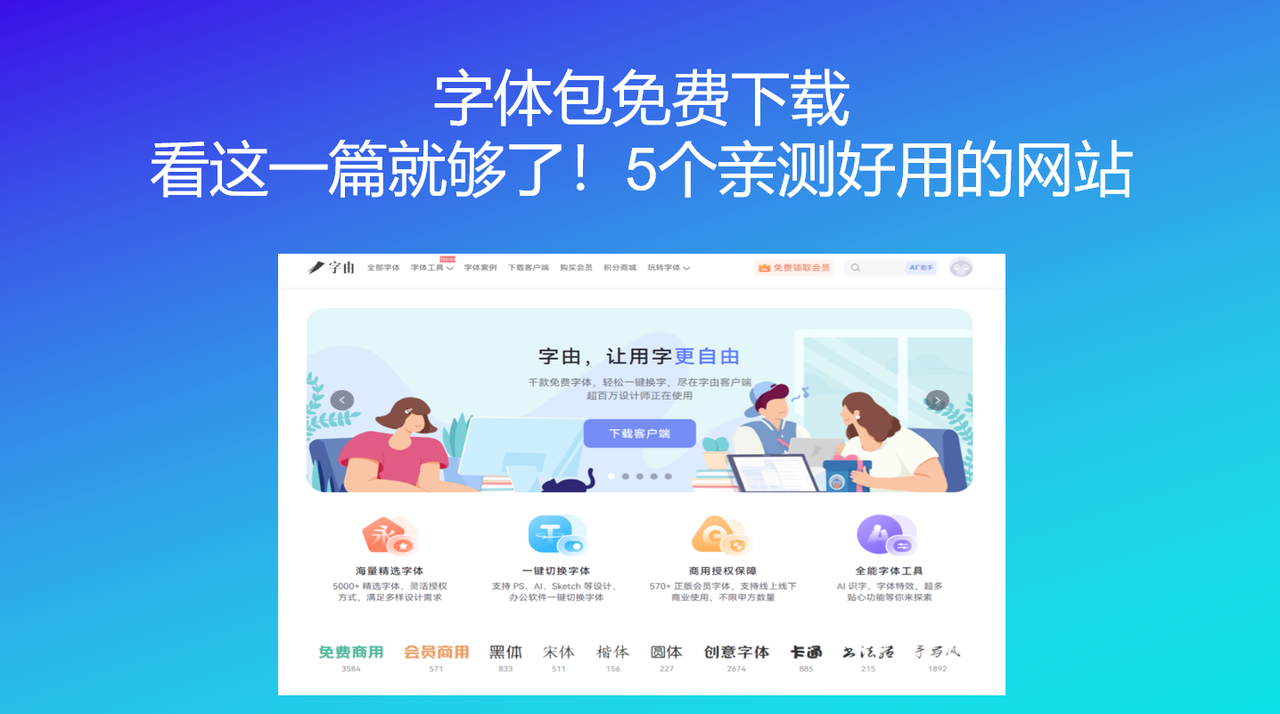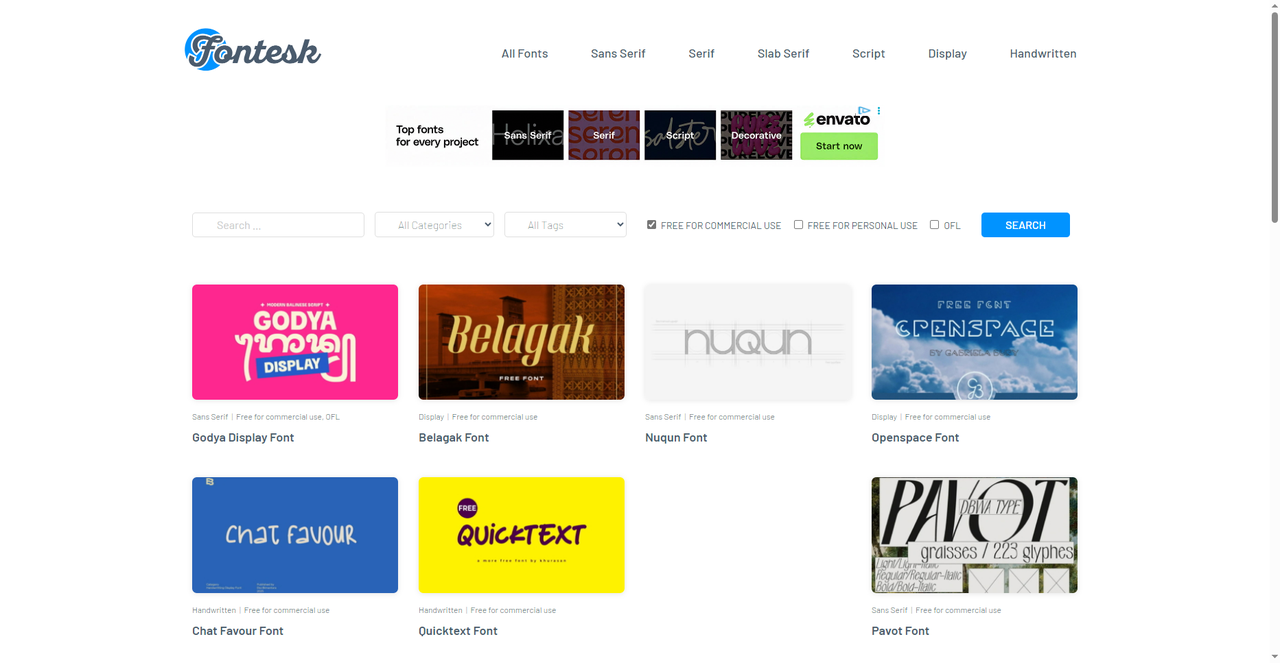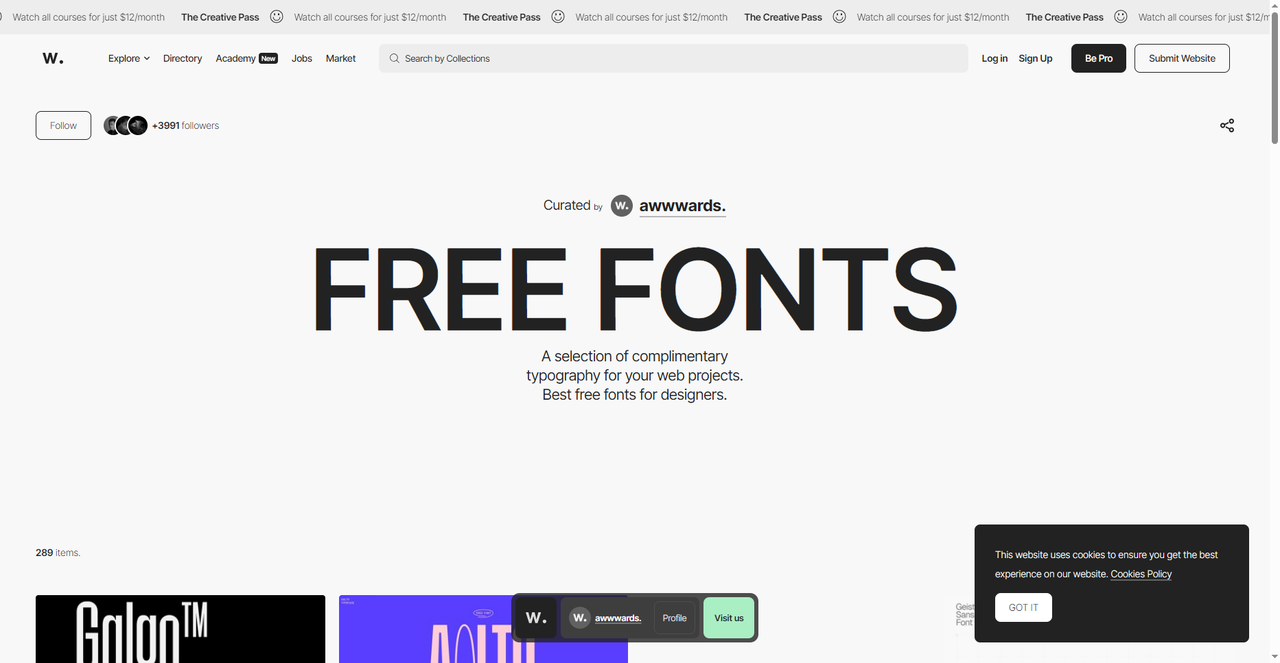
字体包免费下载,看这一篇就够了!5个亲测好用的网站
如果你是做设计的,那么我相信你的硬盘里一定会有专门放字体的文件,不论是自己积累的还是从零散网站里下载的字体,大大小小总应该有好几个 G 了,因为我就是这样。每次真正要用字体的时候需要翻半天并且还不能很准确地找到合适的字体。有时候去网上搜索字体,下载下来以后才发现“仅限个人练习使用”,更是白高兴一场。其实字体包免费下载的资源有很多,关键是找对地方。今天我就整理了 5 个亲测好用的字体包免费下载网站,都是我一个一个踩坑总结出来的,需要的话直接收藏,以后找字体不用再到处翻了!
今天要介绍的第一个字体包免费下载网站是字由。它和普通字体下载网站最大的不同,是它直接把 5000 多款字体打包成了一个“超级字体包”——你不需要一个一个下载、安装,打开客户端就能用。字由所涵盖的字体包本身就已经足够丰富,因为其内置了 5000 多款精选字体,其中超过 3500 款是免费可商用的,每一款都标注了授权类型,用起来特别省事。如果你是团队管理者,开通团队/企业会员后,可以创建团队专属字库。管理员可以上传本地字体或添加字由字体至团队字库,上传后所有成员都能共同使用。对于设计团队、广告公司来说,这个功能能统一团队用字规范,避免每个人各用各的字体导致作品风格不统一。不过就算不开通会员你也依旧可以享用很多优质免费字体包。
2、Fontesk
Fontesk 是一个专门收集免费字体的平台,它的免费商用字体版块规模非常可观——目前收录了超过 6500款 真正免费可商用的字体。并且网站内提供的筛选栏非常便捷,你可以按风格、按标签,甚至是可以按授权类型来筛选,这种非常细致的分类能够帮你快速锁定想要的字体风格。除了常规的风格分类,Fontesk 还有很多“情绪标签”——比如“Edgy”(前卫)、“Bouncy”(活泼)、“Romantic”(浪漫)、“Cyberpunk”(赛博朋克),如果你在做一个有特定调性的项目,但是不知道用什么样的字体,可以试试 Fontesk 里面的字体包,下载也十分方便,安装就可以使用。
3、Awwwards
Awwwards 是全球知名的网页设计奖项平台,每天都会评选出优秀的网站设计。很多人不知道的是,Awwwards 专门整理了一个 “Free Fonts”字体包,收录了289款适合网页项目的免费字体。这个合集里的字体都是经过 Awwwards 团队挑选的,风格偏向现代、简约、有设计感。比如 Geist by Vercel、Pangram Sans Rounded、PP Mori、Harmond 等,都是当下网页设计圈比较流行的字体。点击任意一款字体,可以看到它在网页上的应用效果,如果你在做网页设计或者是 UI 设计,需要一些现代感强、风格明显的字体包,那么Awwwards 的免费字体包值得收藏。
4、Free Typography
Free Typography 是一个专注于分享免费字体和设计资源的博客型网站。从首页可以看到,它主要提供独家免费字体下载、字体推荐和设计访谈等内容。网站的主要特点就是会定期更新最新免费字体,比如首页展示的 Renesnip Sans(由设计师 Jorn Slotboom 提供)和 Victorian Decade(来自 Fontsgood),都是独家下载资源。最主要的是,Free Typography 还有一个很实用的功能——邮件订阅。输入邮箱后可以收到免费的博客更新和独家免费字体,只对订阅用户开放。如果你不想错过好资源,可以考虑订阅。
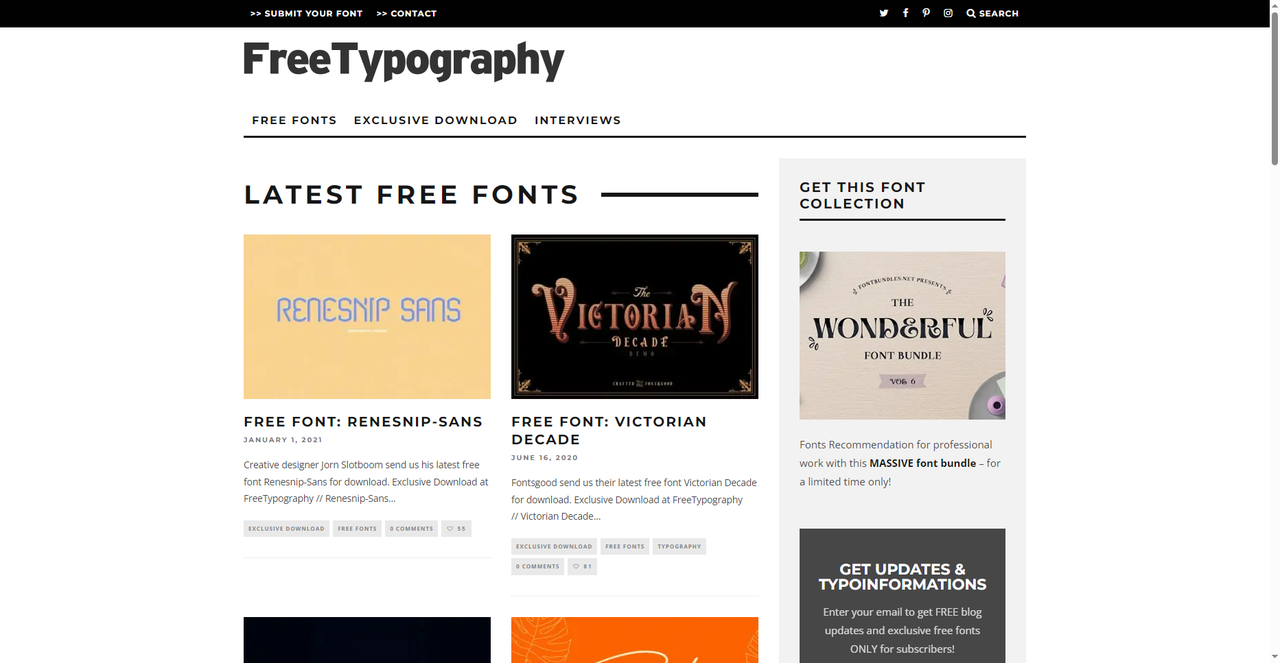
5、Designer Mill
Designer Mill 是一个收集各类免费设计资源的平台,这个网站不仅仅提供字体包免费下载,它主要提供免费的 Figma 模板和 UI 设计资源。可以看到首页推荐了一款名为 Hidrom 的免费显示字体——融合了80年代复古未来主义美学和科幻界面的技术几何感,由设计师 Dazor 制作。每一款字体都有详细的风格描述和下载链接。之前有提到了Designer Mill 还提供 Figma 免费模板,如果有用 Figma 软件的设计师们说不定会更需要这个网站。
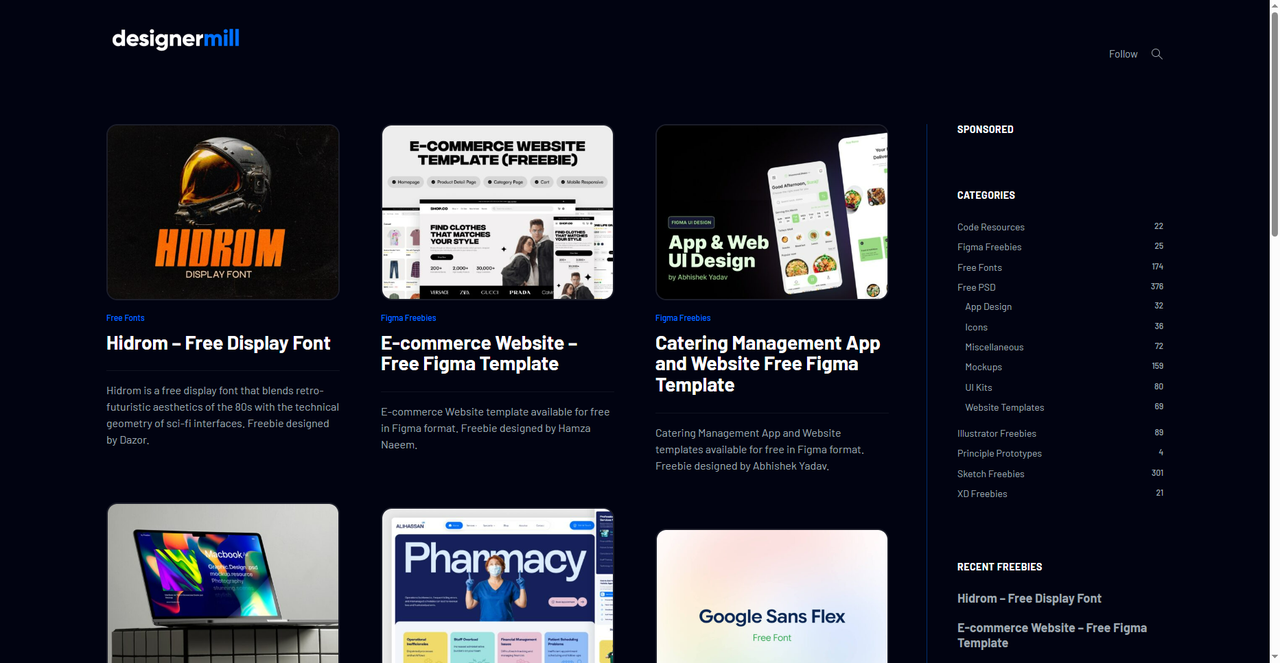
这5个字体包免费下载网站,基本都是非常实用的,Fontesk 数量够多、分类够细;Awwwards 的免费字体包里的字体都是精挑细选的;Free Typography 经常有独家资源,订阅邮件还能收到隐藏福利;Designer Mill 除了字体还能淘到 Figma 模板和 UI 资源。但如果让我选一个日常用得最多、也最省心的,我还是会推荐字由,而且个人云字体库解决了我多设备同步字体库的难题,还方便了团队协作。需要的朋友可以直接点击字由官网链接来试一试!